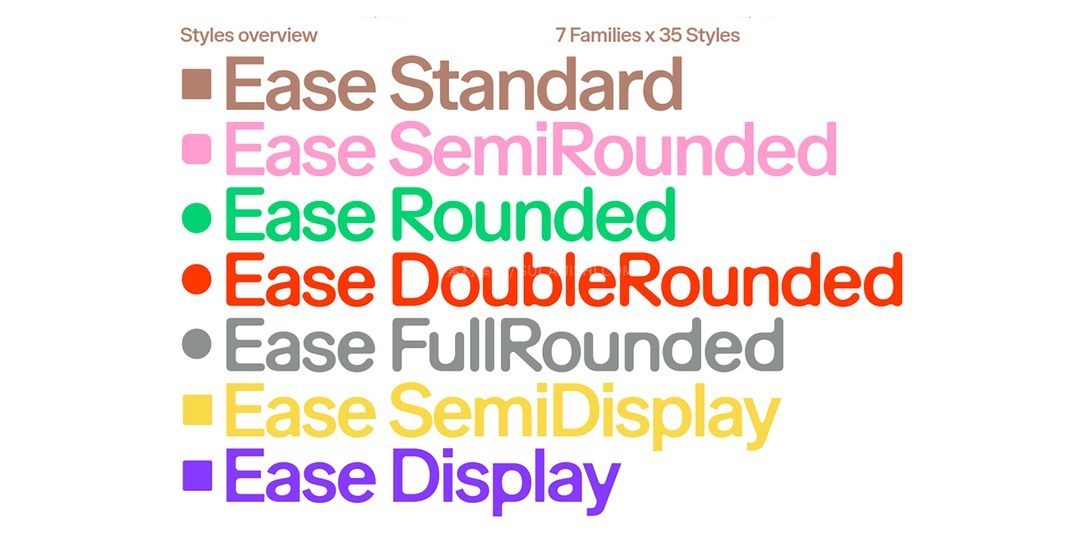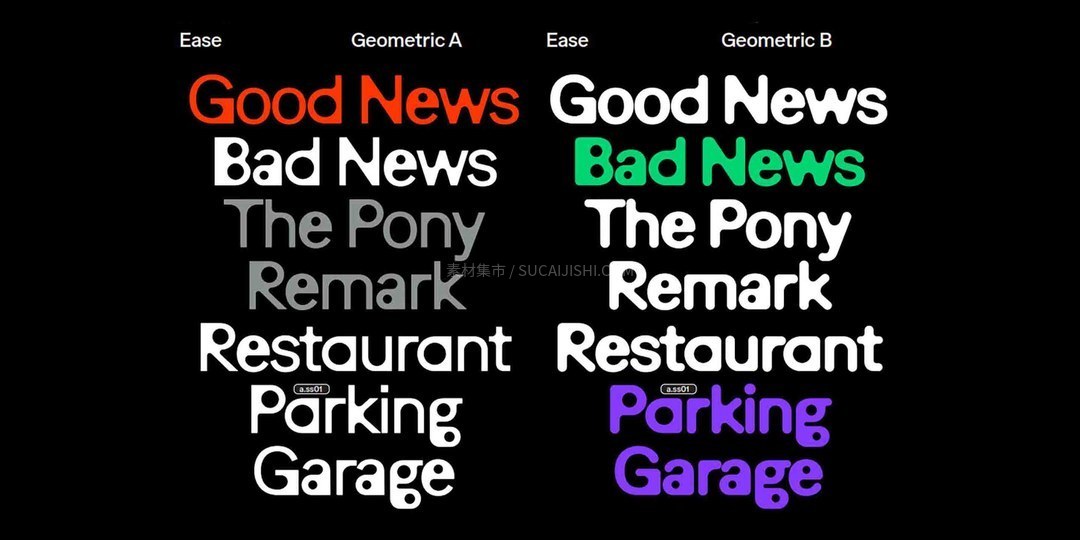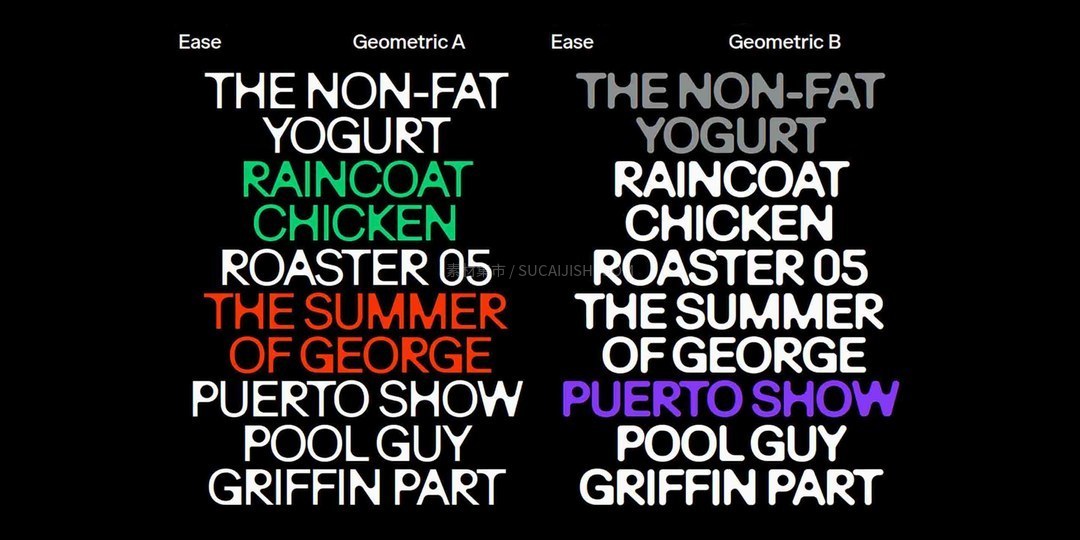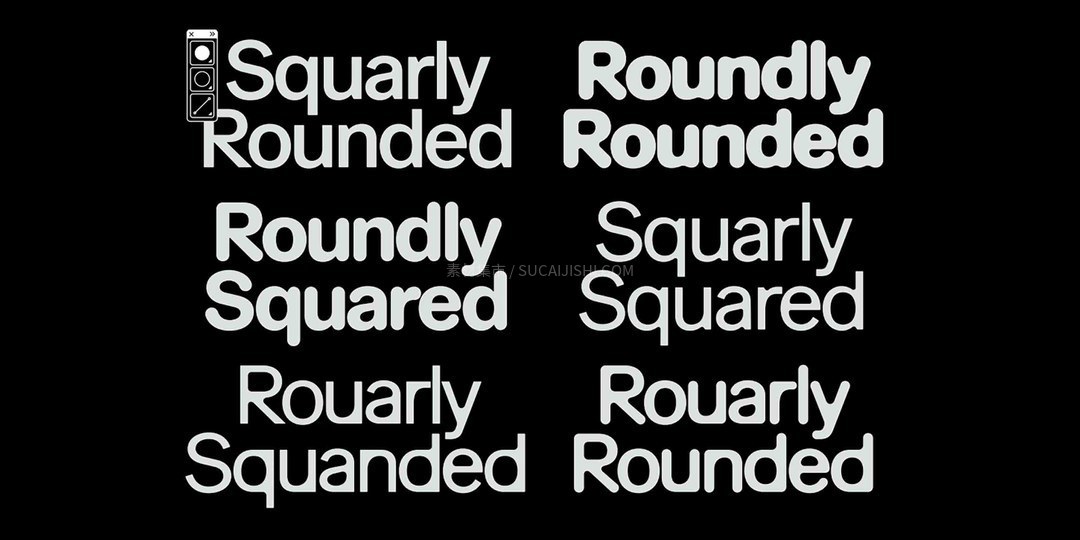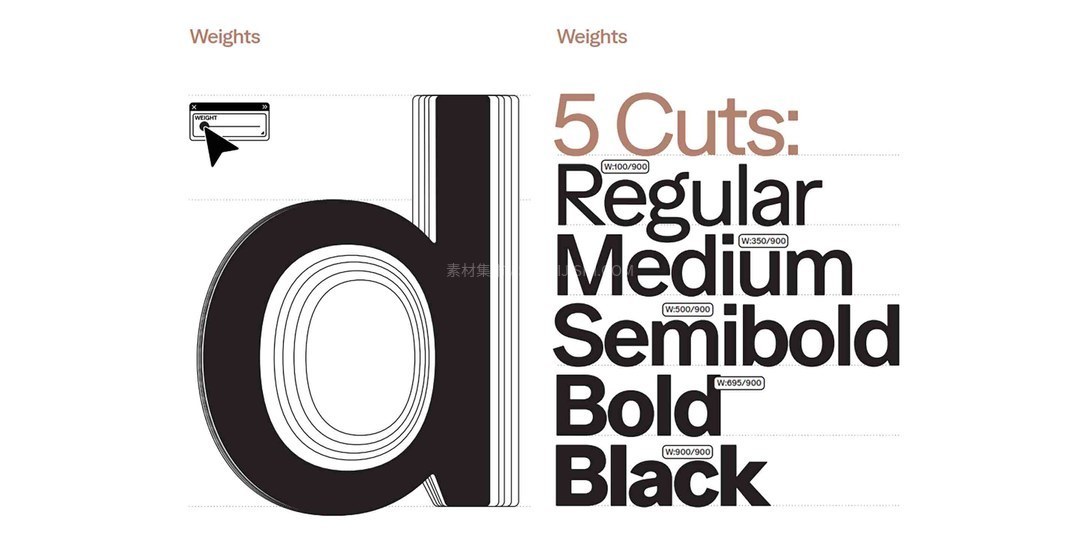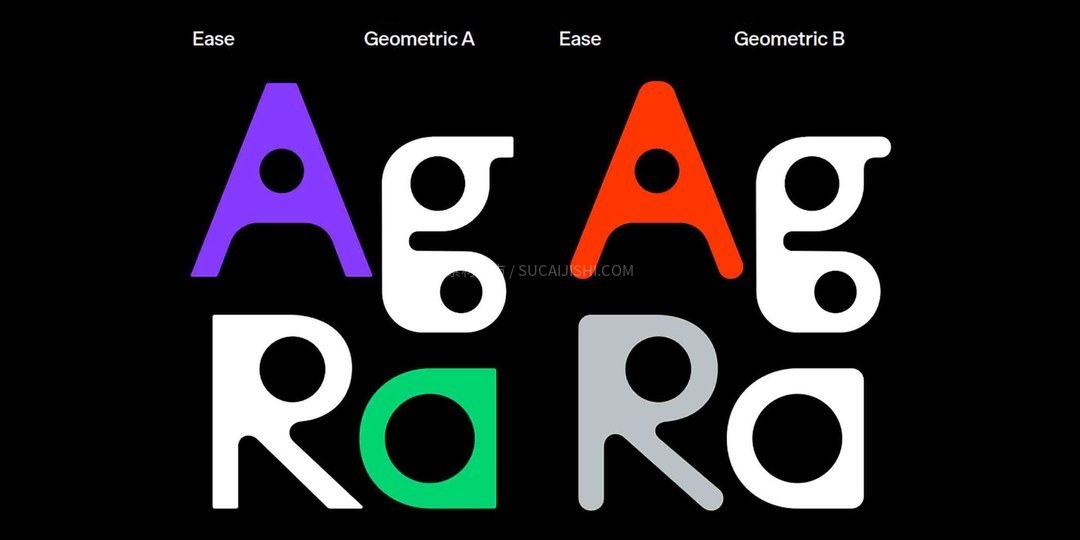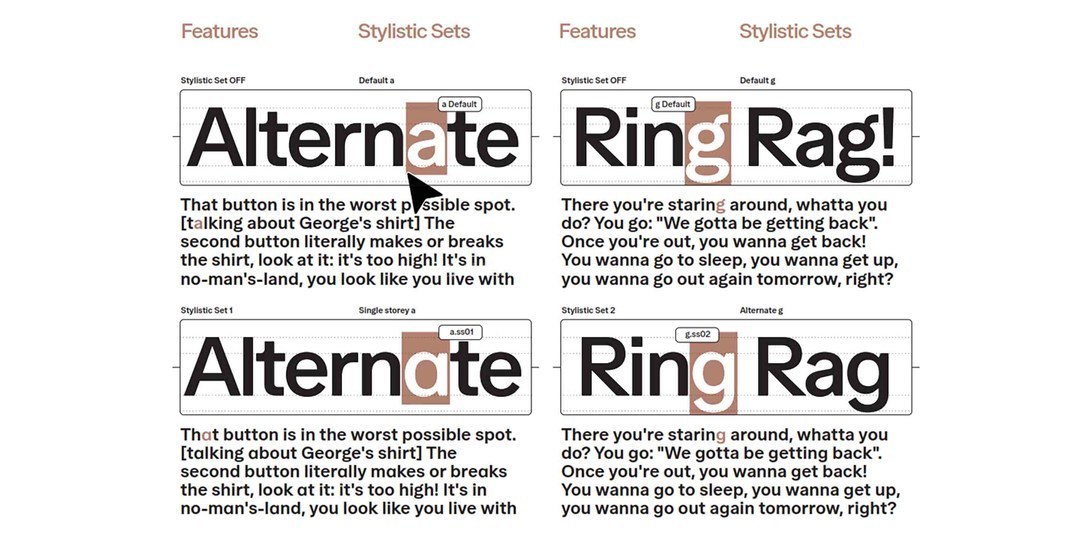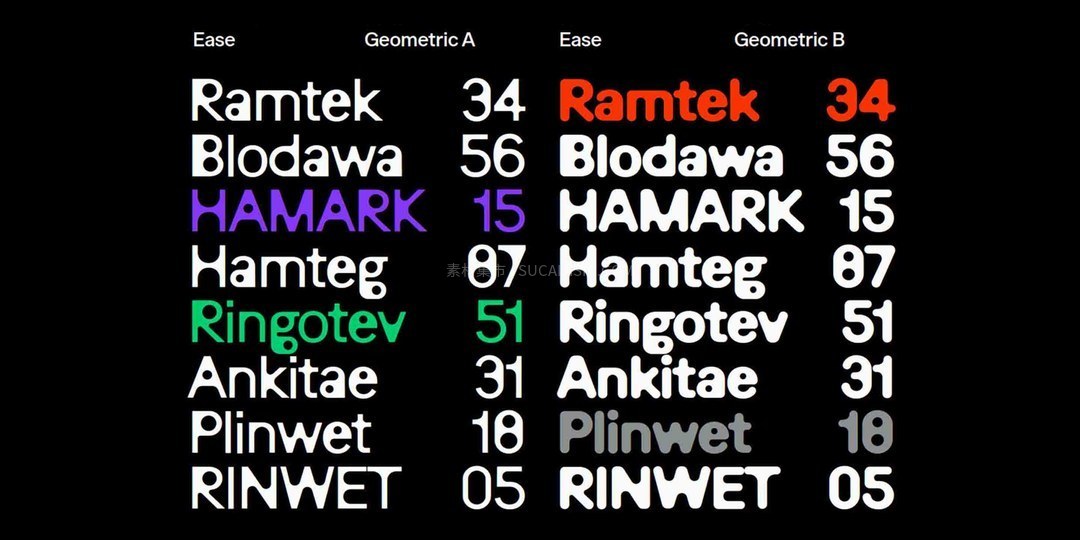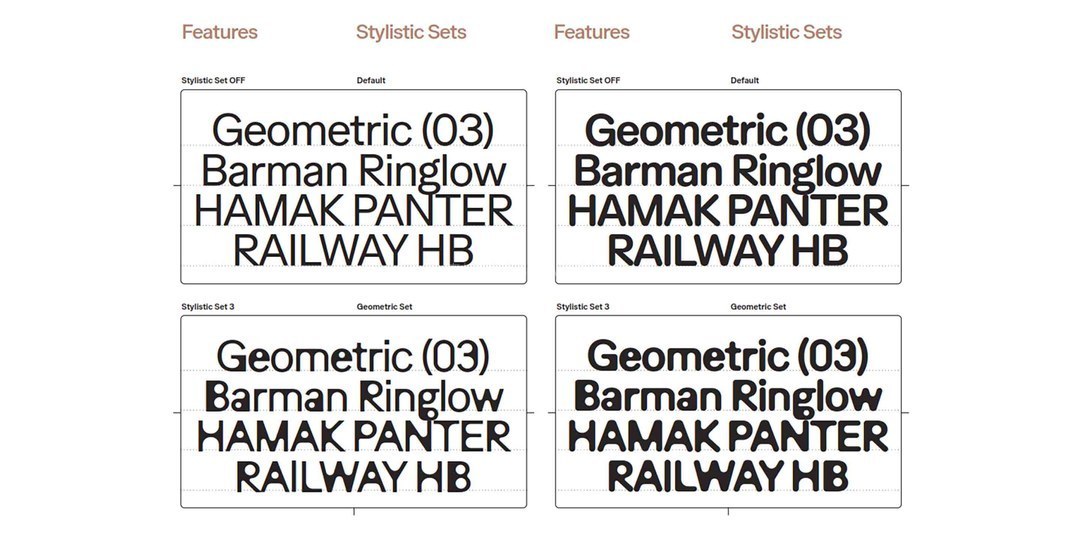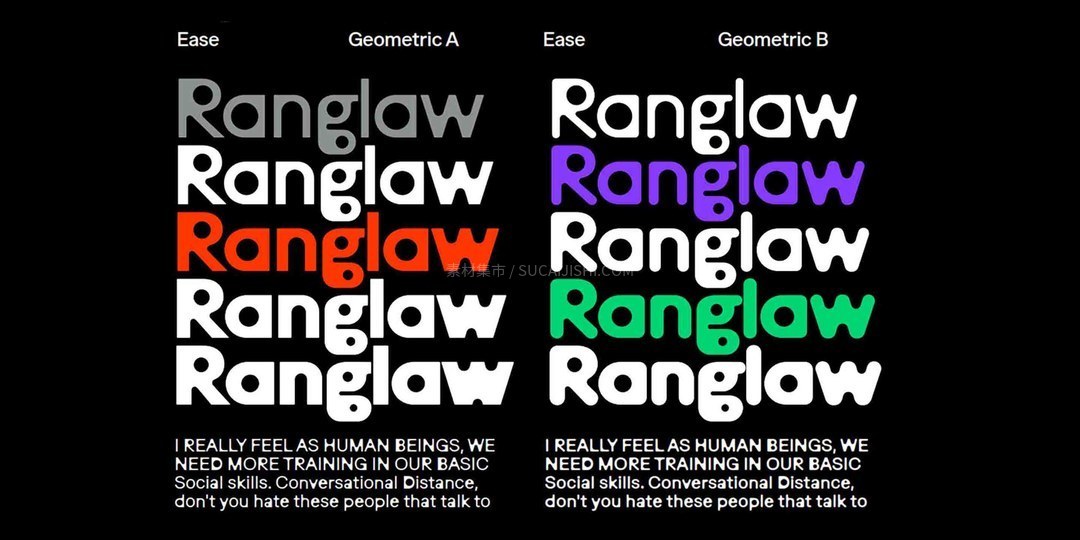
Ease全能可变字体家族
Ease 是一款功能强大、极具现代感的专业字体家族,为您提供前所未有的排版自由。这套系列包含 35 种精心打磨的静态样式,以及 1 款高度灵活的可变字体(Variable Font)。从纤细优雅的极细体到极具视觉冲击力的超粗体,Ease 能够无缝过渡,满足您对字重、字宽的任何严苛要求。这套字体不仅能极大提升跨设备平台的设计效率,更能为您的排版注入专业、精致的视觉质感,让每一处文字细节都张弛有度。